一转眼2021即将结束2022也要到来。回顾2021年上首造字团队不断地进行市场调研和探索创新,已经在字体视界平台发布了100+款新品商业授权字体,每一款字体都极具个性,深受用户喜欢。
赶着2021年的脚步,喜迎2022年,字体视界携手上首造字为广大设计师朋友们奉上最后一波上首新品字体,希望可以为您新一年的作品设计锦上添花,赶紧喊您的小伙伴一起来接收吧!
上首纤宋体,字体轻柔纤细,每一个字都仿佛是一名少女翩翩起舞。适用于搭配标志、广告标语、商业广告等高端属性。
新年第一天,怎么可以没有安排一张关于元旦的祝福呢?元旦快乐海报送给大家,希望大家在新的一年里每天都快快乐乐!
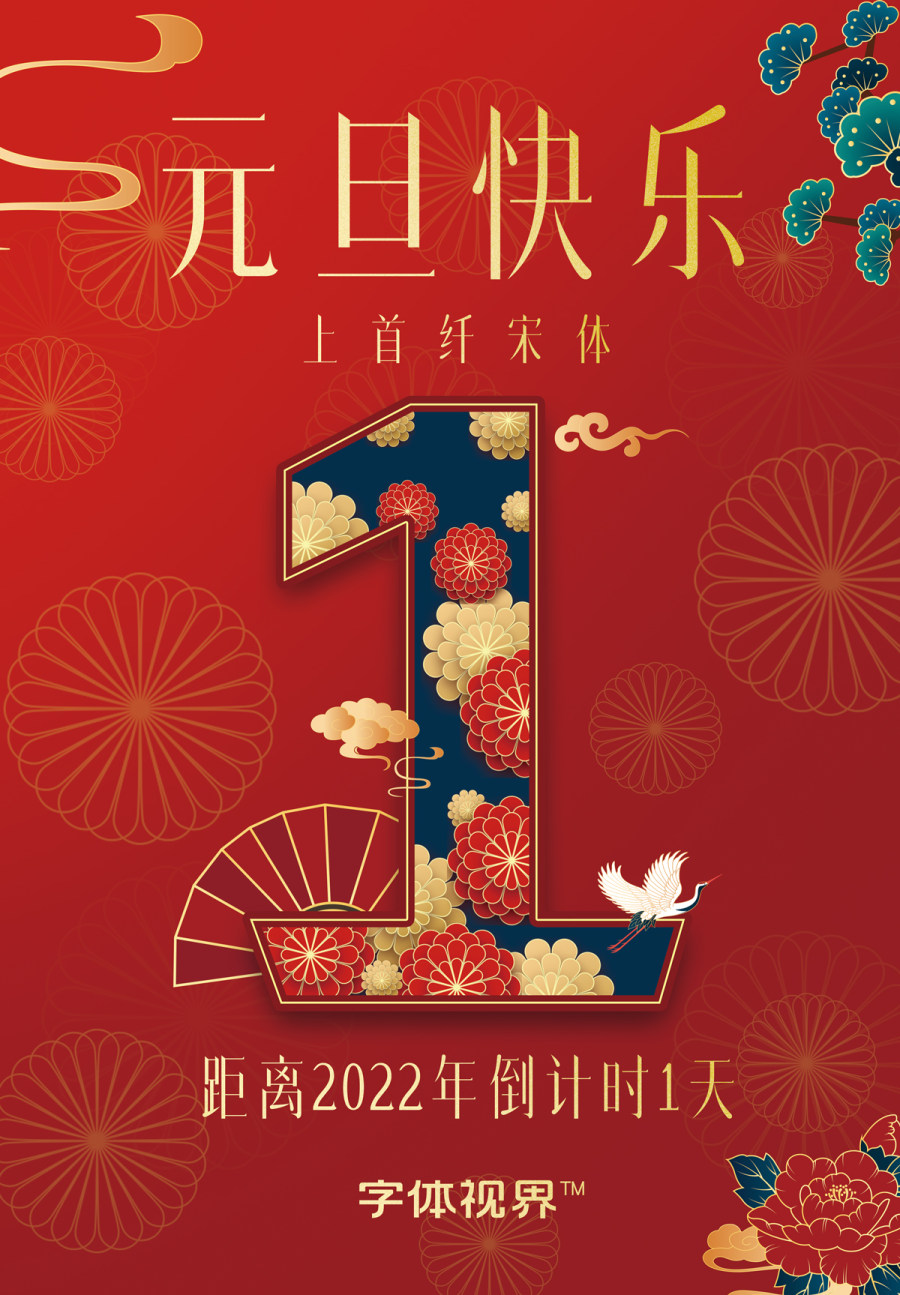
上首星际体,简体中文约6763字,其字形曲折刚正,特点颇多,宛如从钢铁中切割而出,像是宇宙飞船的装甲外壳,又如机器的零件,让人联想到在星际中航行的飞船舰队,富有科技感。适用于搭配标志、广告标语、商业广告等高端属性。
不管是元旦快乐还是新年快乐,简单的海报中寄予这一份新年的祝福,希望2022年的你们都是快乐的吉祥的